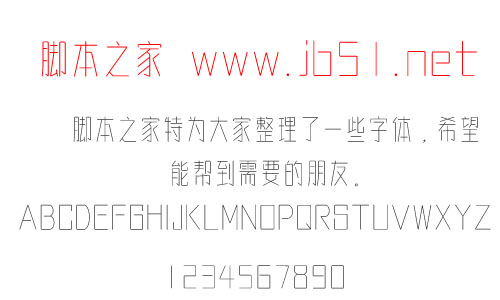
劉兵克曦冉體超細(xì)版是一款設(shè)計(jì)優(yōu)美、風(fēng)格簡約的美術(shù)字體,字形修長,線條纖細(xì)干凈,整體設(shè)計(jì)有創(chuàng)意,用作美術(shù)字體非常棒,特點(diǎn)鮮明,適用于各類時(shí)尚品牌的廣告設(shè)計(jì)與包裝。但是辨識度較低,不適合用于排版印刷,歡迎喜歡劉兵克曦冉體超細(xì)版的朋友前來下載使用。